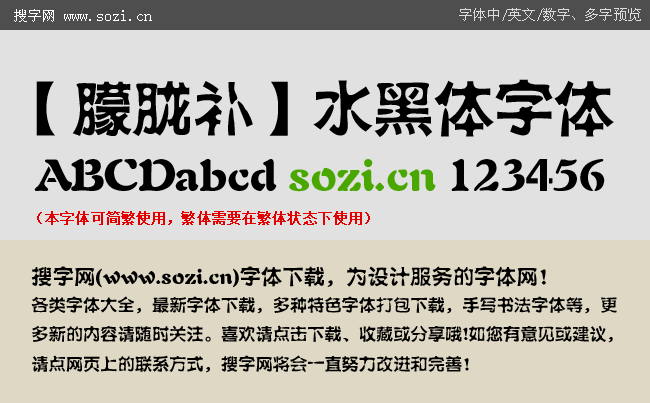
水黑體字體
搜字網(wǎng)給大家提供一款水黑體字體手機(jī)卡通中文字體下載。水黑體是一款帶有水滴效果的POP風(fēng)格中文粗字體,由粗黑體做為原字體進(jìn)行藝術(shù)變形,非常的厚實(shí),保持黑體端正粗壯的風(fēng)格同時(shí)增強(qiáng)趣味性,適合追求手機(jī)個(gè)性應(yīng)用的朋友下載使用。